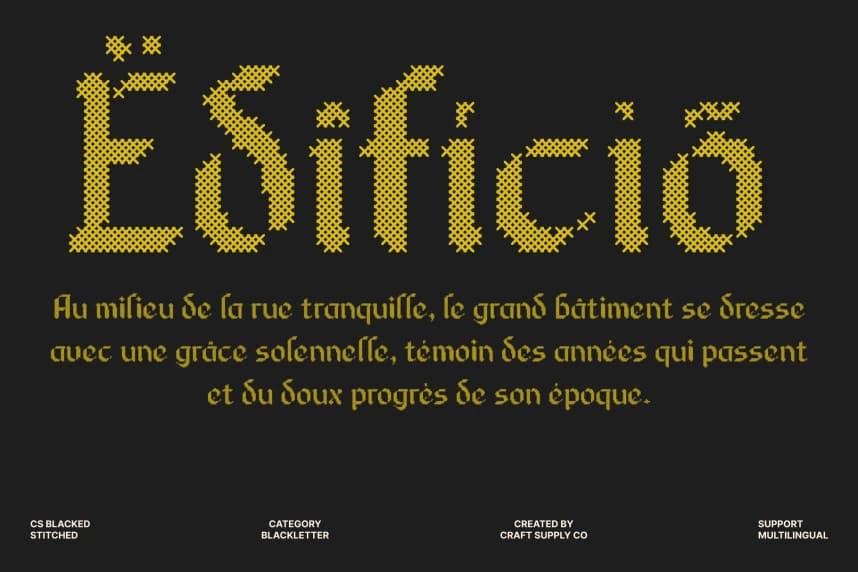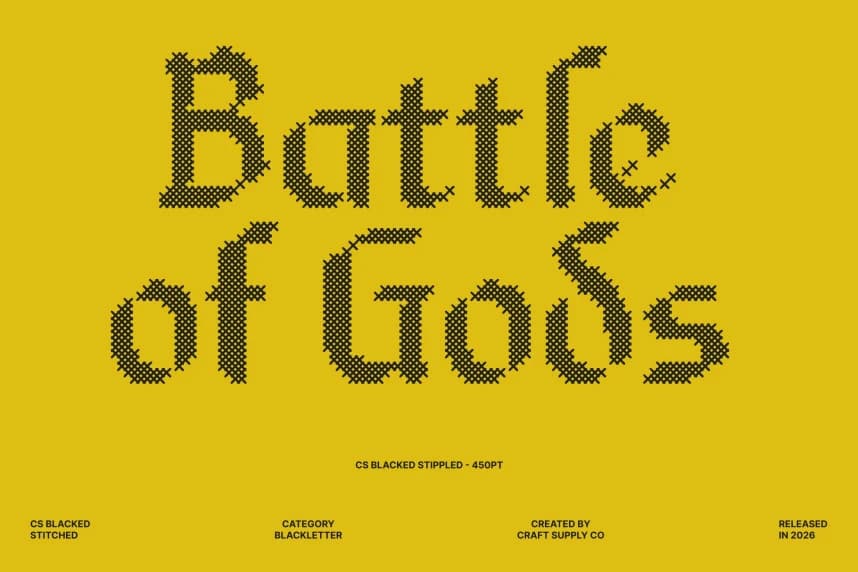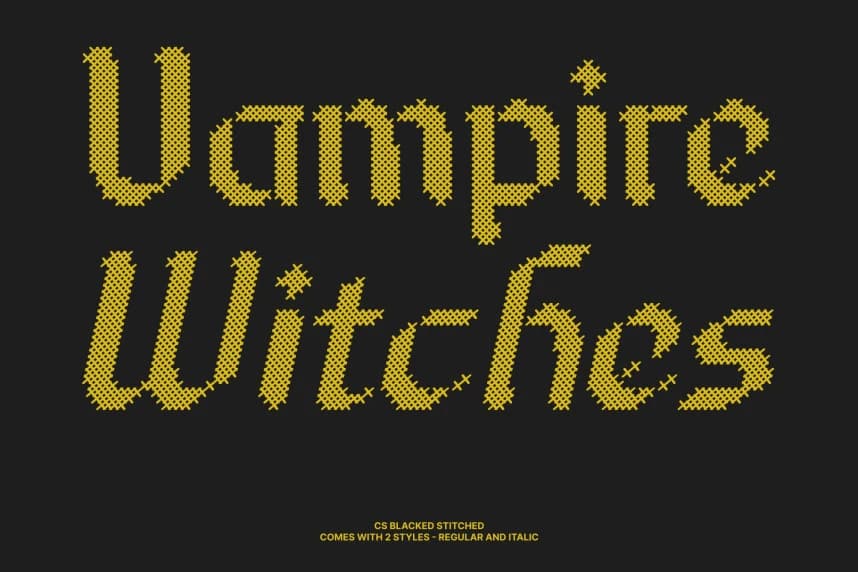
CS Blacked Stitched Font
CS Blacked Stitched Font – Blackletter Yazı Tipi: Tarihî Cazibeyle Klasik Zarafeti Buluşturan Blackletter Gösterim Serif Yazı Tipi, El Yapımı Karakterlerle. Bu, geleneksel Gotik tipografinin zamansız zarafetini kucaklayan çarpıcı bir Blackletter Gösterim Serif yazı tipidir.
CS Blacked Stitched Font – Blackletter Font: Tarihî Çarpıcılığa Sahip Klasik Zarafet Blackletter Display Font ile El Yapımı Karakterli. Bu, geleneksel Gotik tipografinin zamansız zarafetini kucaklayan çarpıcı bir Blackletter display serif yazı tipidir.